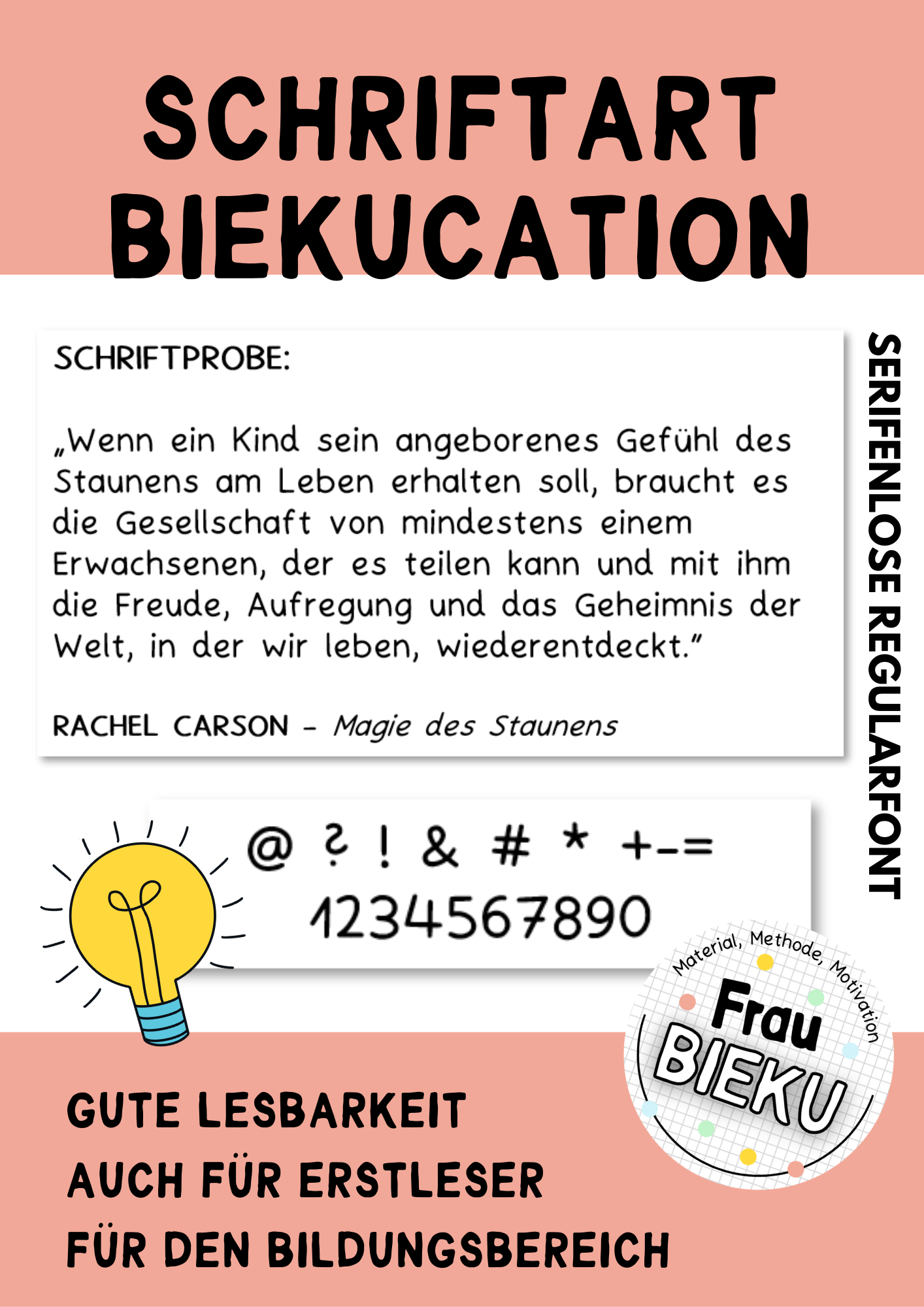
Biekucation ist eine serifenlose Schrift, die ich speziell für den Bildungsbereich entwickelt habe. Sie ist lebendig und ruhig zugleich, sodass sie auch für Erstleser einfach zu erfassen ist.